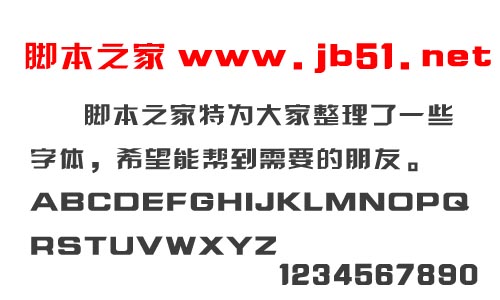
包图创意体是包图首款公益字体,该款字体共收容6763个简体汉字,26个大写字母,26个小写字母,10个阿拉伯数字,及32个常用标点及符号。它适用于教育、工业、文学杂志、影视制作以及内容用字等领域,可用作电商设计、LOGO设计、包装设计等。设计师及社会各界都可登陆包图官网进行免费下载商用。欢迎喜欢此款字体的朋友前来下载使用。